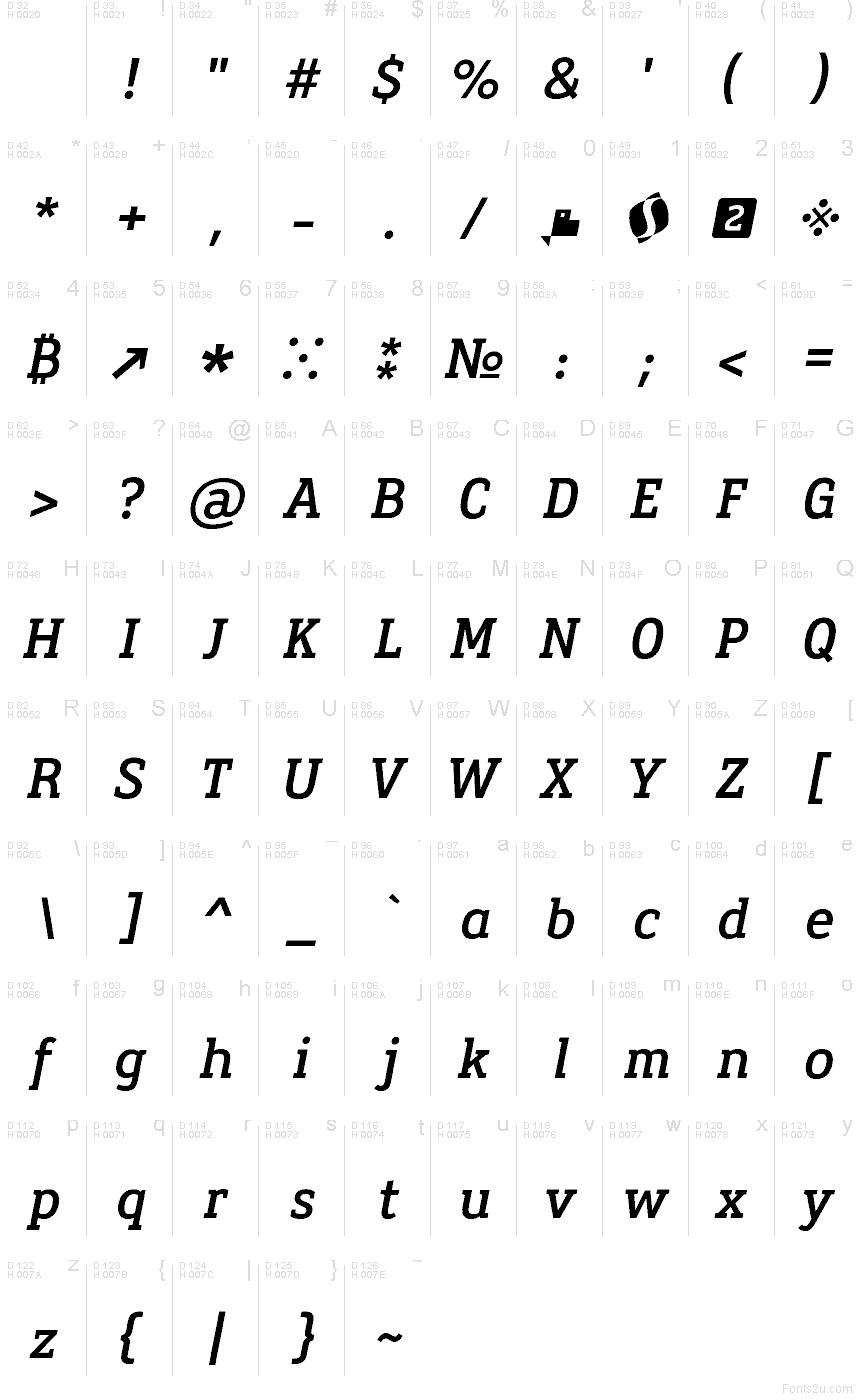
Biotrip Serif Medium Italic
Biotrip Serif Italic de deFharo é uma fonte serif gratuita com uma inclinação acentuada e uma silhueta cortante, que lembra o papel recortado. As letras misturam traços em forma de cunha com detalhes de serifa pontiagudos, conferindo ao design um ritmo tenso e aerodinâmico, fugindo da fluidez suave comum em muitas itálicas serifadas.
Esse ímpeto clipped a torna uma excelente escolha para capas de livros de ficção científica, títulos de jogos, manchetes de pôsteres, capas de álbuns e branding que exija um toque literário estilizado. Linhas curtas são as que mais se beneficiam, onde as formas anguladas e as uniões abruptas estruturam um título ou logótipo sem cair no território comum das serifas clássicas.